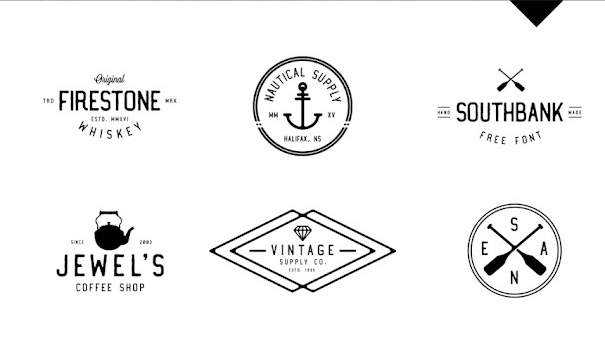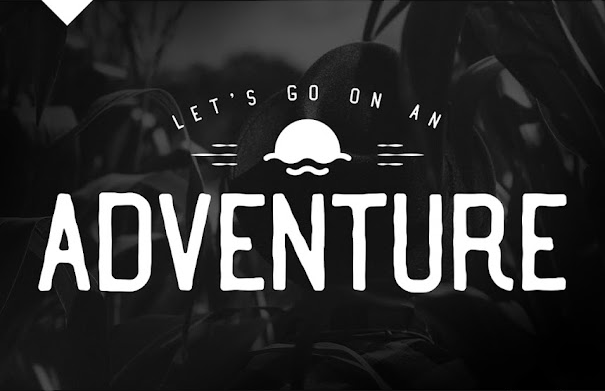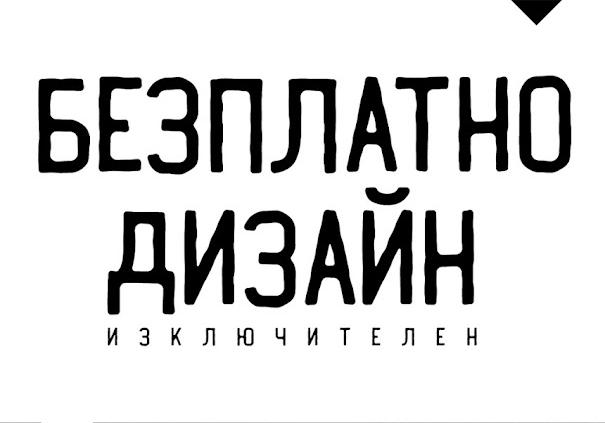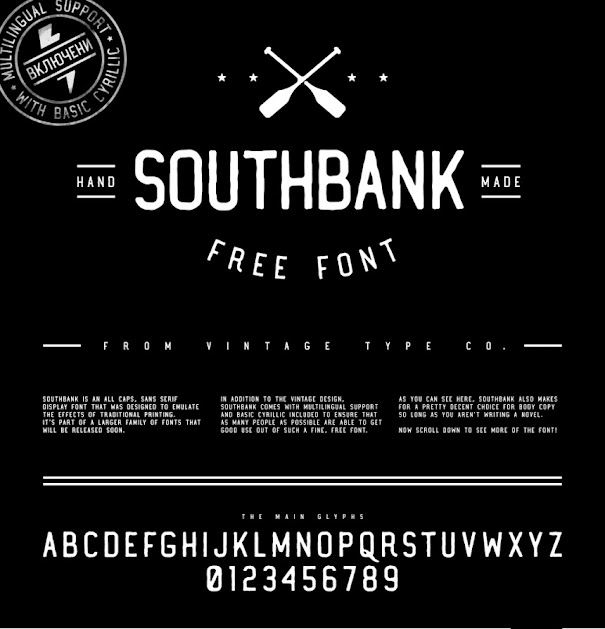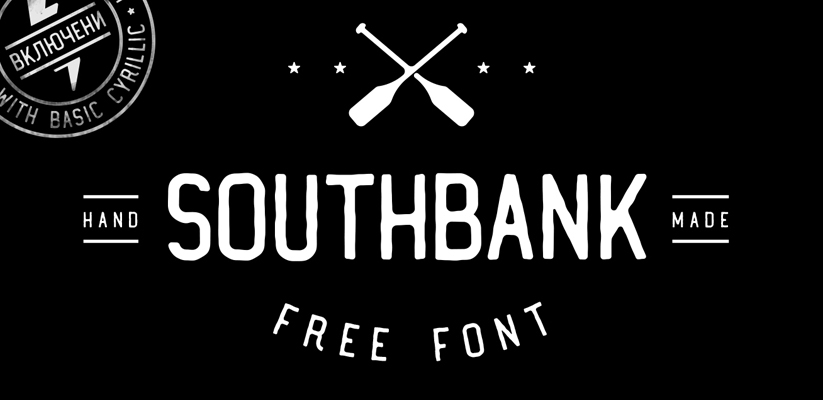
Free Fonts – Southbank
Southbank LT: Font Bebas yang Menampilkan Pesona Cetak Tradisional
Dalam dunia desain grafis, pemilihan font yang tepat dapat menjadi kunci keberhasilan sebuah proyek. Banyak desainer mencari font yang tidak hanya estetis, tetapi juga memiliki karakter unik dan mudah dibaca. Southbank LT hadir sebagai salah satu pilihan menarik bagi para desainer yang menginginkan tampilan klasik dengan sentuhan modern.
Southbank LT adalah font sans serif display yang sepenuhnya menggunakan huruf kapital (all caps) dan didesain untuk meniru efek-efek yang dihasilkan oleh teknik cetak tradisional. Font ini dikembangkan secara gratis, sehingga dapat diakses dan digunakan oleh siapa pun tanpa biaya.
Keunikan Southbank LT terletak pada karakternya yang tegas dan elegan, dengan detail halus yang mengingatkan pada proses pencetakan huruf konvensional. Bentuk hurufnya yang sederhana namun kuat membuatnya cocok untuk berbagai aplikasi desain, mulai dari judul poster dan spanduk hingga logo dan identitas brand.
Kelebihan Southbank LT antara lain:
• Tampilan Klasik: Desain font ini meniru efek cetak tradisional, memberikan kesan vintage dan elegan.
• Mudah Dibaca: Meskipun berjenis sans serif, Southbank LT tetap mudah dibaca dalam berbagai ukuran teks.
• Versatile: Cocok digunakan untuk berbagai jenis desain, baik digital maupun cetak.
Southbank LT merupakan pilihan tepat bagi desainer yang menginginkan font bebas dengan karakter unik dan tampilan klasik. Ketersediaannya secara gratis menjadikannya aset berharga bagi siapa pun yang ingin mengeksplorasi kreativitas dalam desain grafis.
Southbank LT is free all caps, sans serif display font that was designed to emulate the effects of traditional printing.